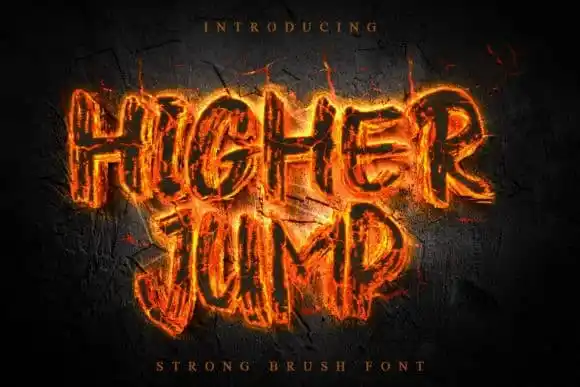
A fonte ‘Higher Jump Brush Font’ é uma escolha perfeita para projetos que desejam transmitir sofisticação com elegância natural. Desenvolvida por Thomas Aradea, essa tipografia brush tem um toque único e belo, atraente tanto para designers profissionais quanto para aqueles que buscam uma fonte atraente para uso em logotipos e mensagens de marca. Seu formato feito à mão combina suavidade com rusticidade criando um design poderoso. A ‘Higher Jump Brush Font’ é ideal para qualquer projeto de marca ou frase, oferecendo um toque pessoal que tornará seus designs mais inconfundíveis e memoráveis. Com uma variedade de letras, cada letra destaca-se por seu único e belo aspecto. Seja você um designer profissional ou alguém buscando algo atraente para seus trabalhos de marca, esta fonte é definitivamente uma escolha inteligente que complementará perfeitamente qualquer projeto.